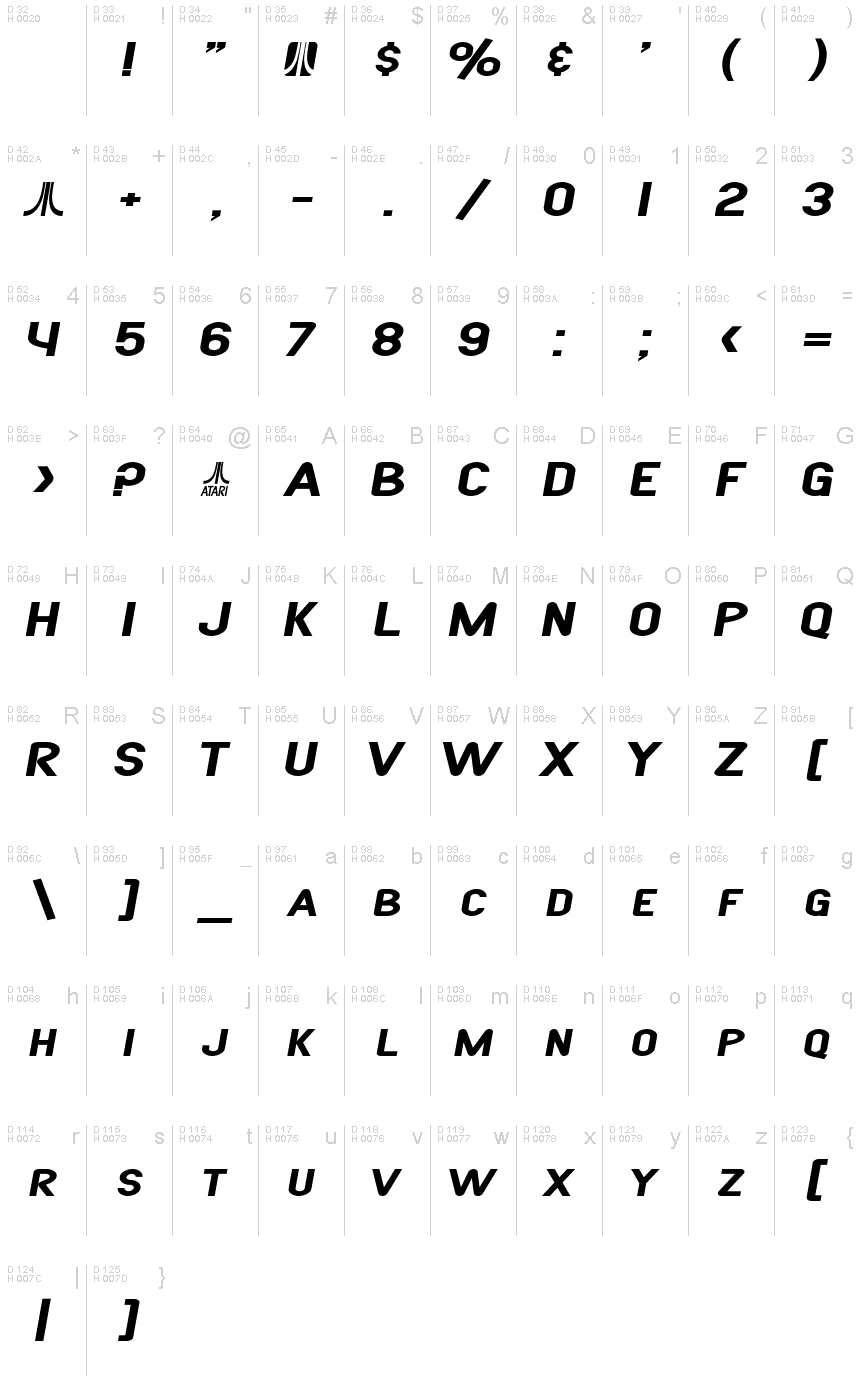
SF Atarian System Extended Bold Italic
SF Atarian System Extended Bold Italic to wyjątkowy krój displayowy z rodziny SF Atarian System, stworzony z precyzją przez ShyFonts Type Foundry. Ten font emanuje futurystyczną aurą, łącząc smukłe linie z wyrazistą grubością i lekko poszerzoną konstrukcją, które przyciągają uwagę. Kursywa dodaje dynamizmu, co czyni go doskonałym wyborem do projektów wymagających nuty nowoczesności i postępowego charakteru.
Charakterystyczne kształty liter przywodzą na myśl cyfrową erę, budząc skojarzenia z zaawansowaną technologią i innowacją. Styl extended bold italic poprawia czytelność, jednocześnie nadając każdemu tekstowi wyrazisty, pewny styl. Niezależnie od tego, czy wykorzystasz go w brandingu, kampaniach reklamowych czy prezentacjach multimedialnych, SF Atarian System Extended Bold Italic z pewnością zrobi niezapomniane wrażenie.
Łącząc estetykę z funkcjonalną wszechstronnością, ten font jest idealny dla projektantów chcących nadać swoim pracom futurystyczny klimat bez utraty czytelności. Wznieś swoje projekty na wyższy poziom wyrafinowania dzięki SF Atarian System Extended Bold Italic – krojowi pisma, który nie tylko powstał z myślą o dzisiejszych czasach, ale został zaprojektowany z myślą o przyszłości.